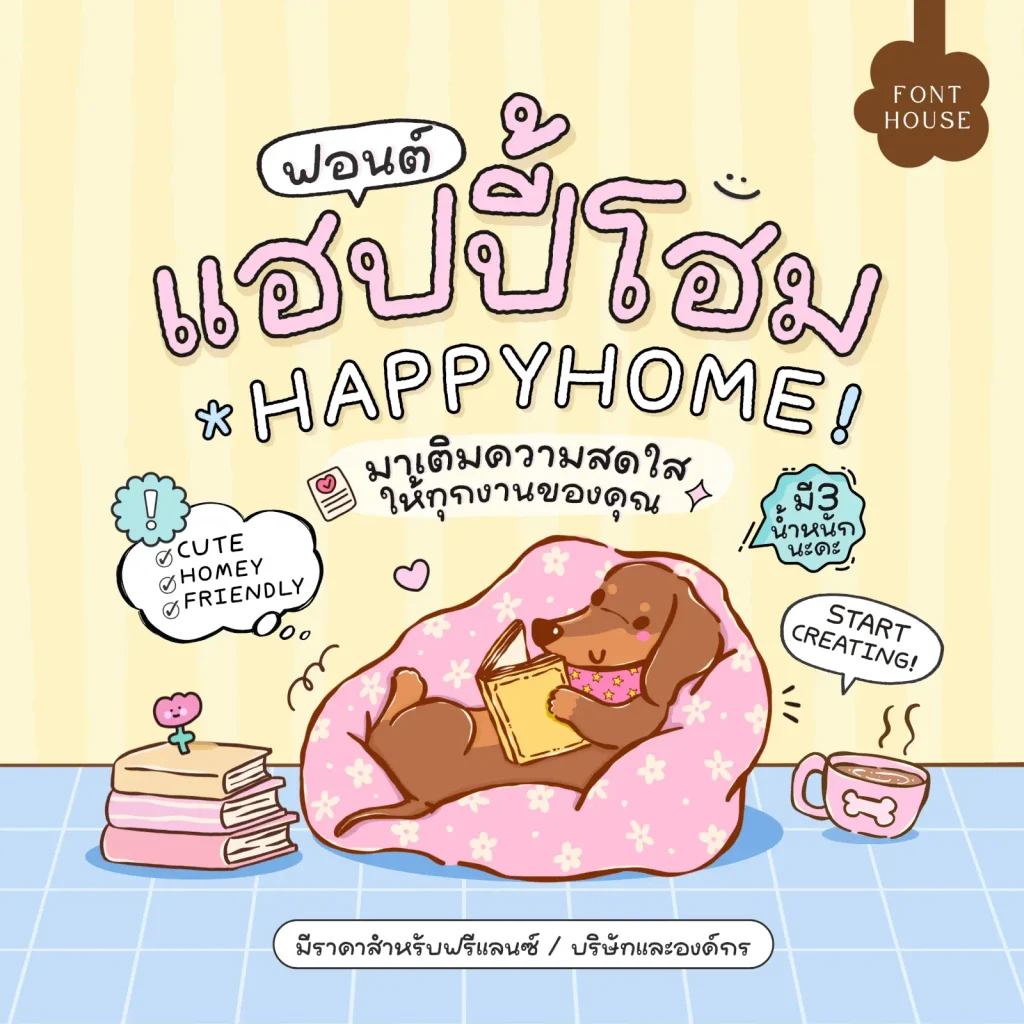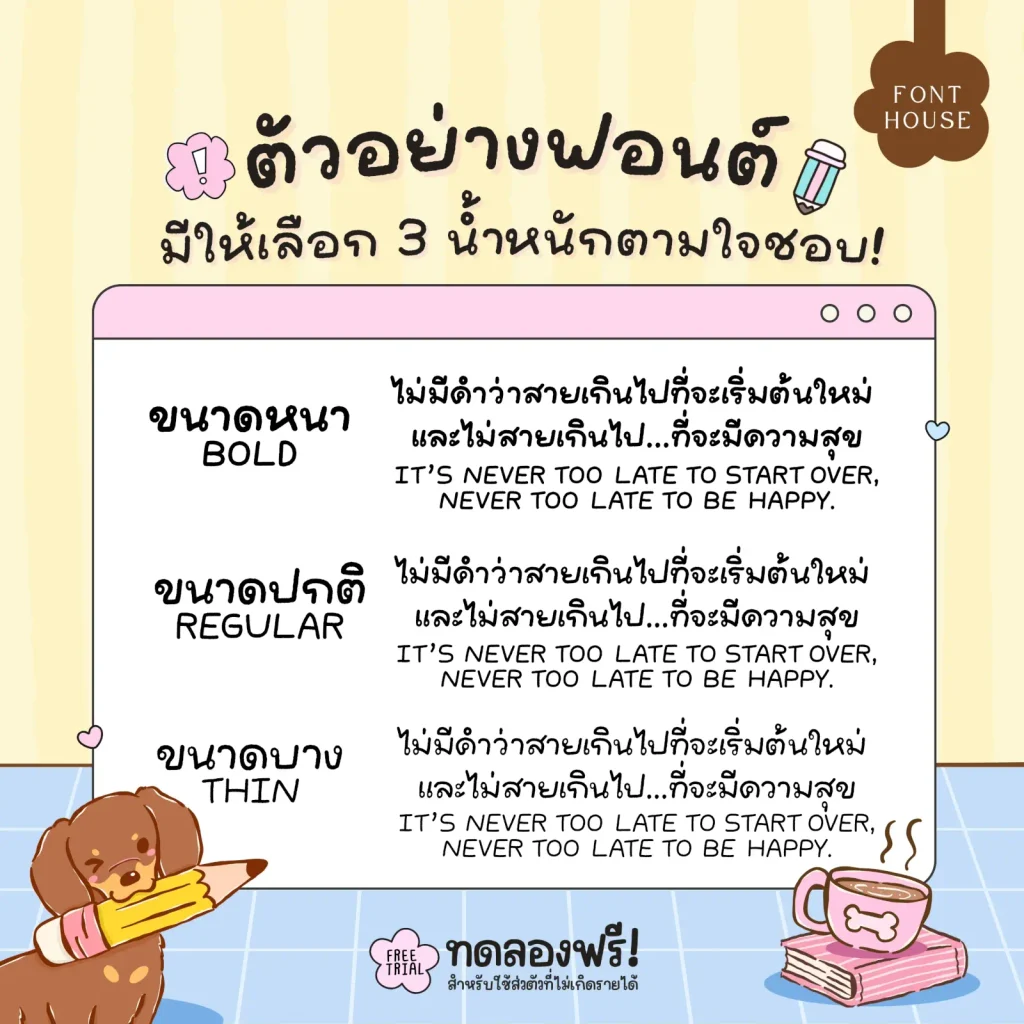
ฟอนต์ แฮปปี้โฮม (FH HAPPYHOME) – ลายมือสไตล์น่ารัก ให้ความรู้สึก ซุกซน สดใสและเป็นกันเอง เรียบง่ายแต่มีคาแรกเตอร์ มีความสนุก ขี้เล่นนิดๆ ช่วยเพิ่มชีวิตชีวาและความสดใสให้กับงาน
- มี 3 น้ำหนัก
แฮปปี้โฮม (FH HAPPYHOME)